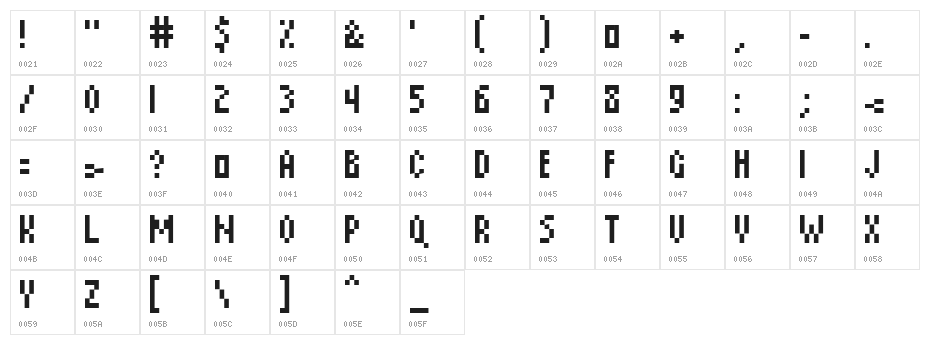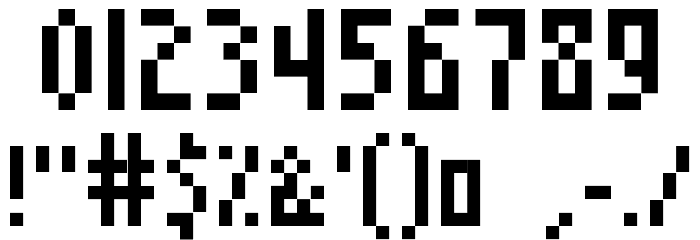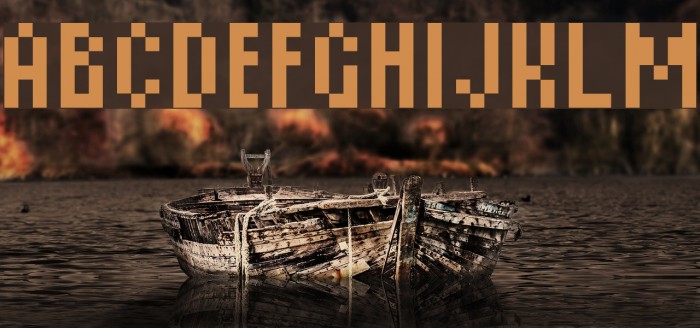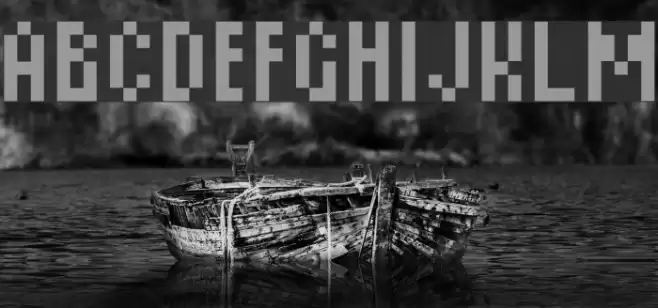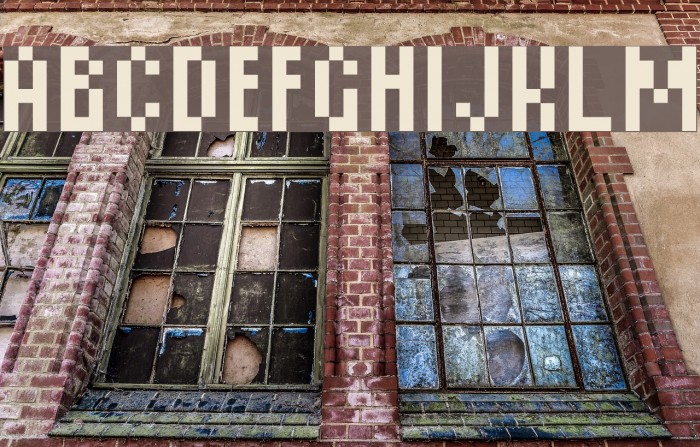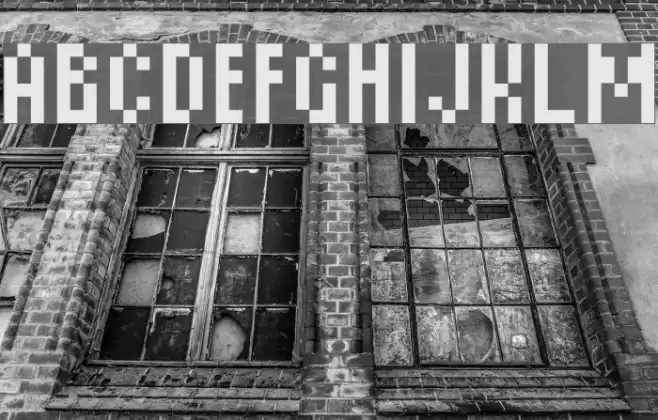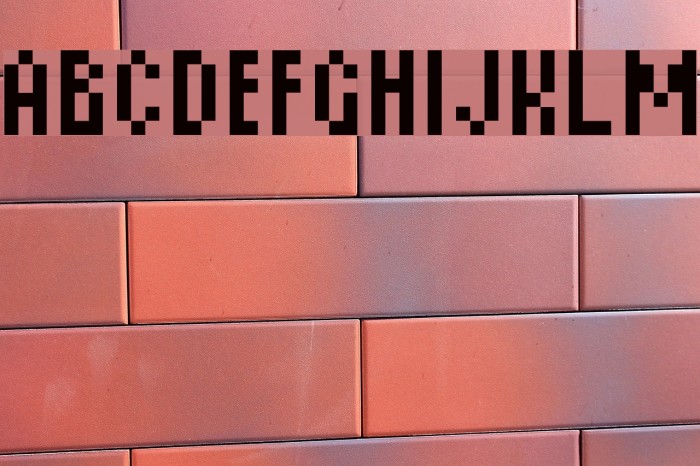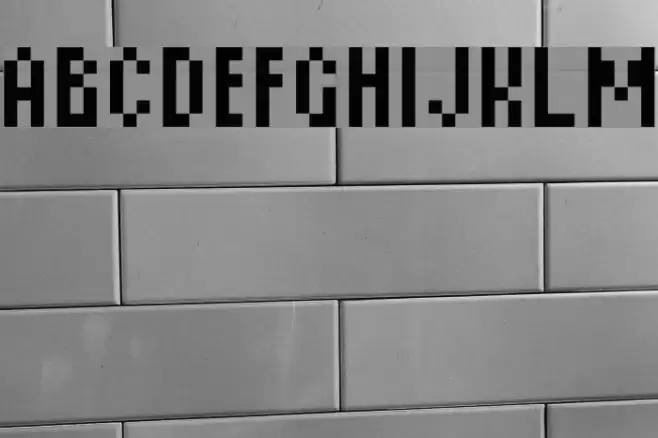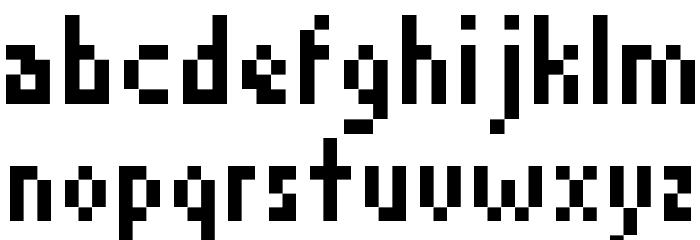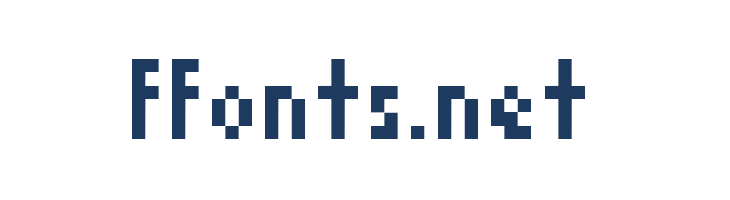
David Device Font
✎ Pixel
| समग्र शैली | Retro, Digital |
| उपयोग का मामला | Headlines, Logos, Posters |
| सुझाए गए प्रोजेक्ट | Ideal for video game design, retro-themed posters, digital art, and tech-related branding. |